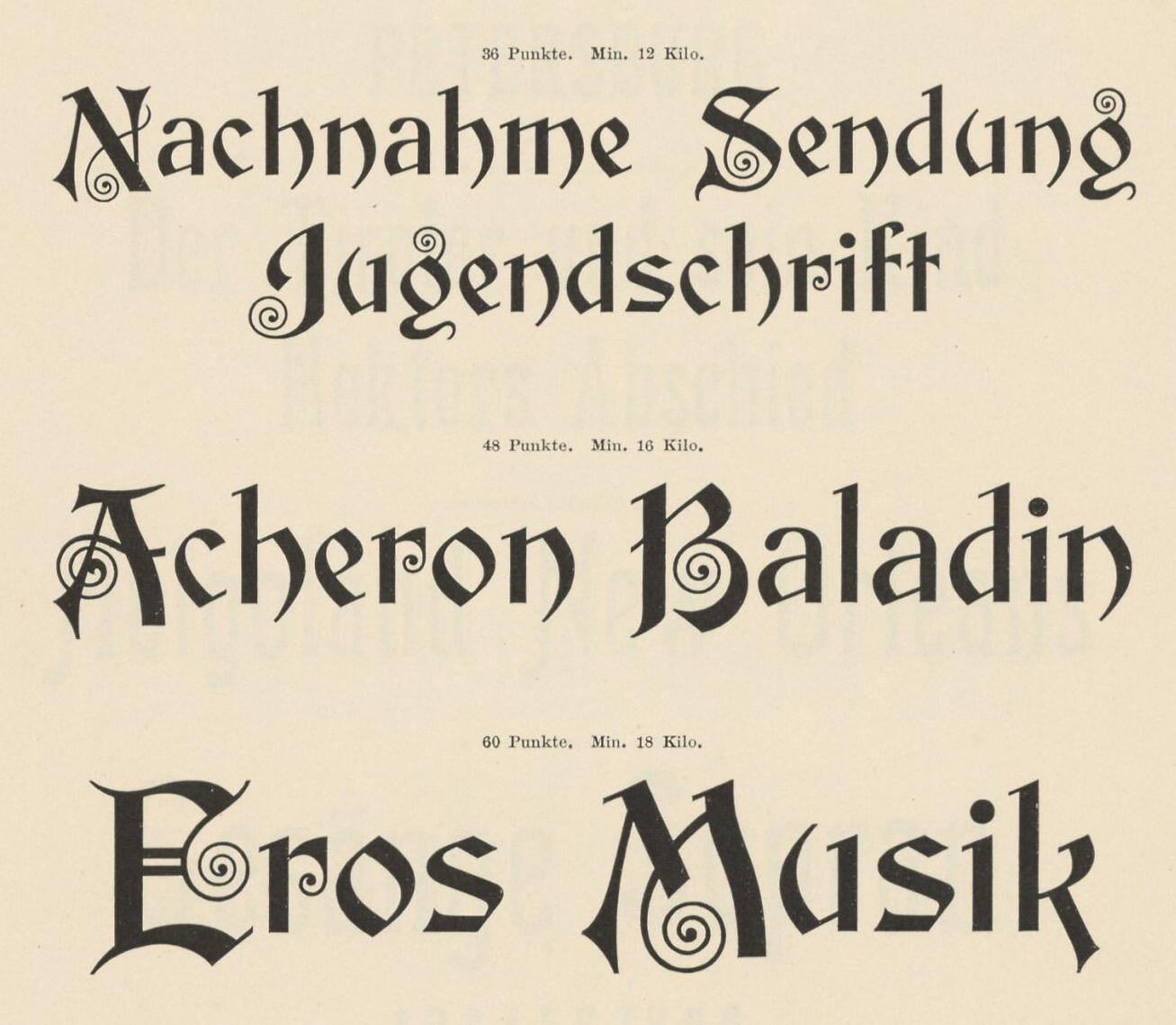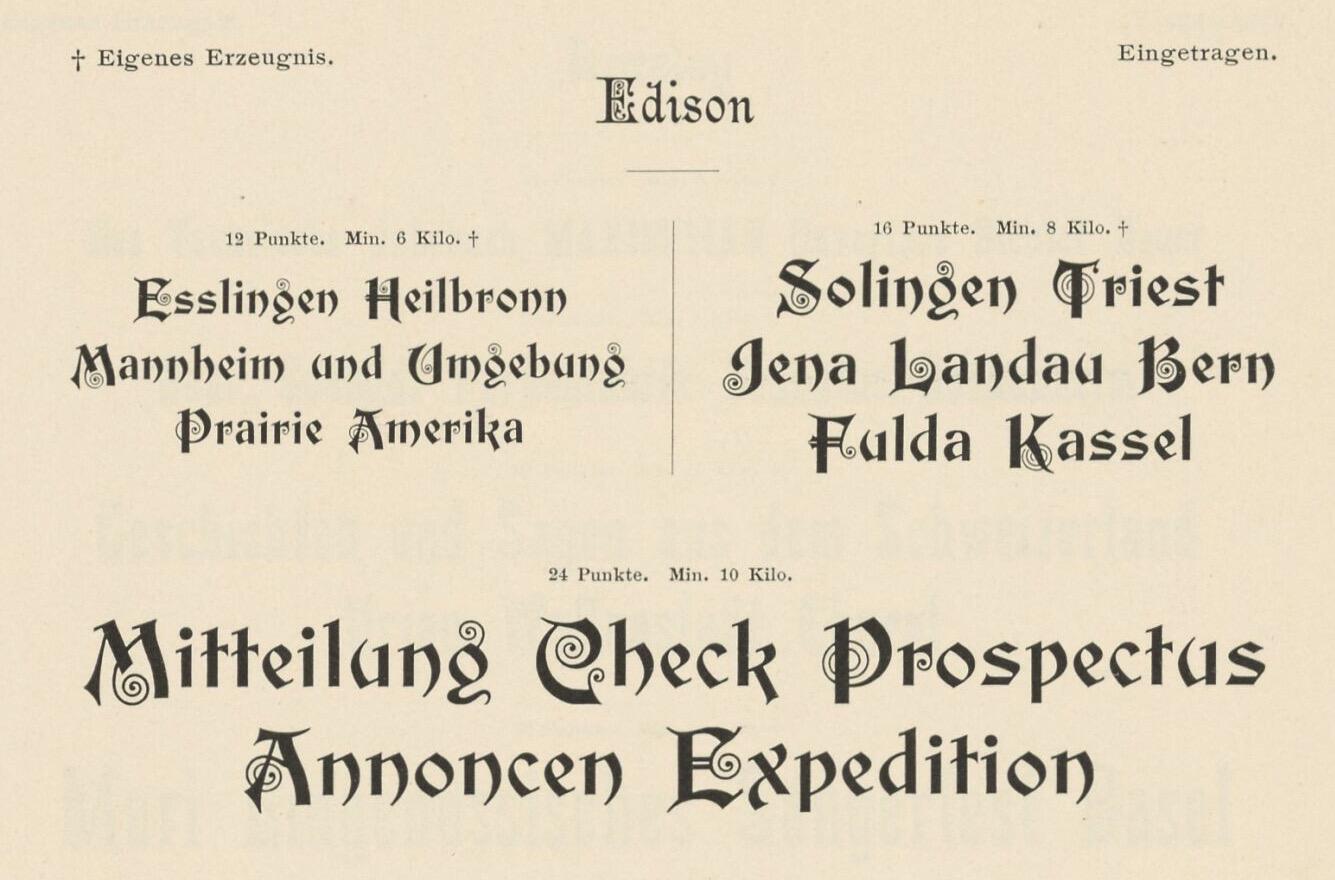
- circa 1894
- Antiqua dekorativ
Diese Schrift wurde von Hermann Ihlenburg entworfen und in den 1890er-Jahren als Houghton über MacKellar, Smiths & Jordan (später American Type Founders) verkauft. In Deutschland erschien die Schrift als Edison über Bauer und Co. (später Berthold). Die Schrift erschien außerdem als Kosmos bei Trennert und Markoni bei Theinhardt.
Die Schrift ist aber insbesondere unter dem Namen Edison bekannt, der auch von den verfügbaren Digitalisierungen durch Spiece Graphics (Edison Swirl SG) and HiH benutzt wird.